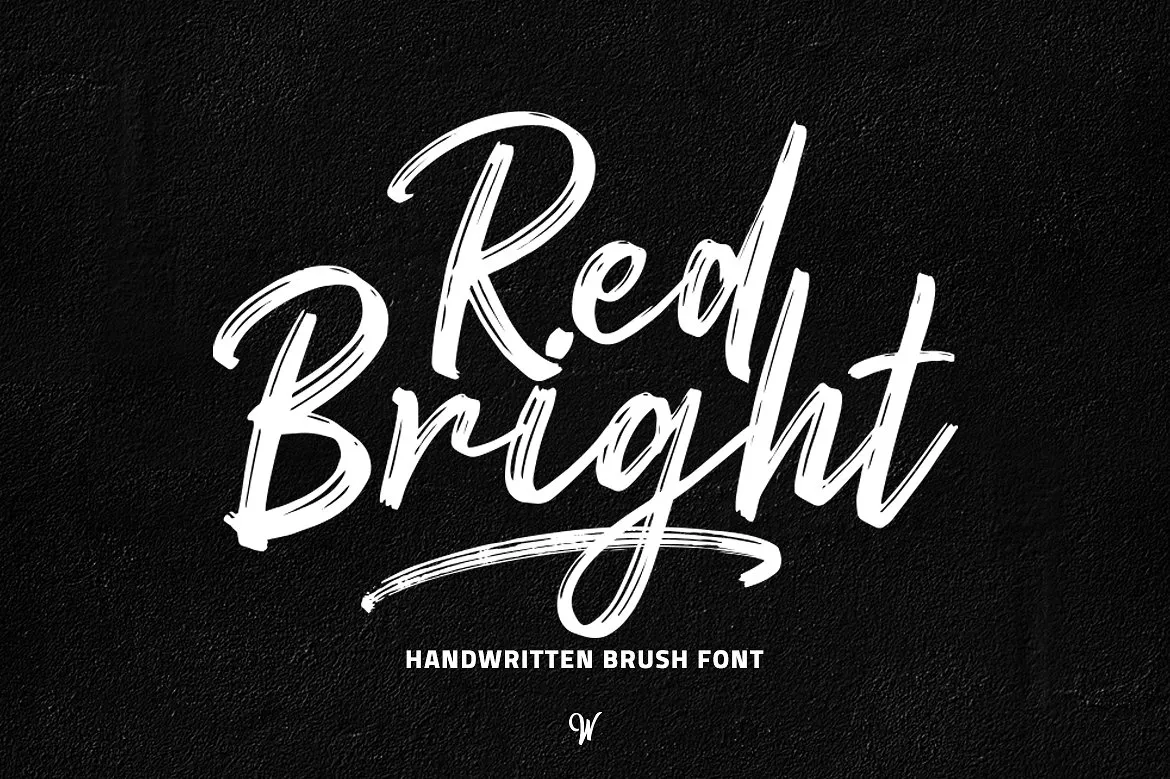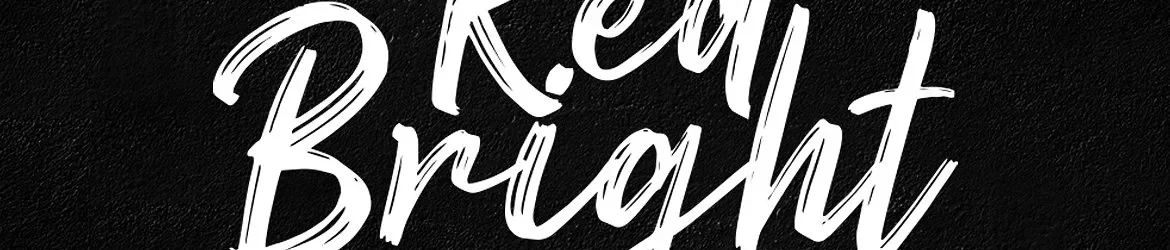
Red Bright Brush Font – Download Grátis
Esta é uma fonte feita a mão com uma pena a lã. Introduzimos Red Bright Font. Com seus traços naturais e desgastados, parecidos com um pincel à mão rápido, ela é perfeita para diversas aplicações. Seja você estilizando materiais promocionais ou escrevendo frases em letra cursiva, criando embalagens de produto ou projetos de marcação. Red Bright oferece uma variedade única e aconchegante que combina bem com um leque amplo de usos. Não perca esta oportunidade para trazer alegria à sua identidade visual e design.